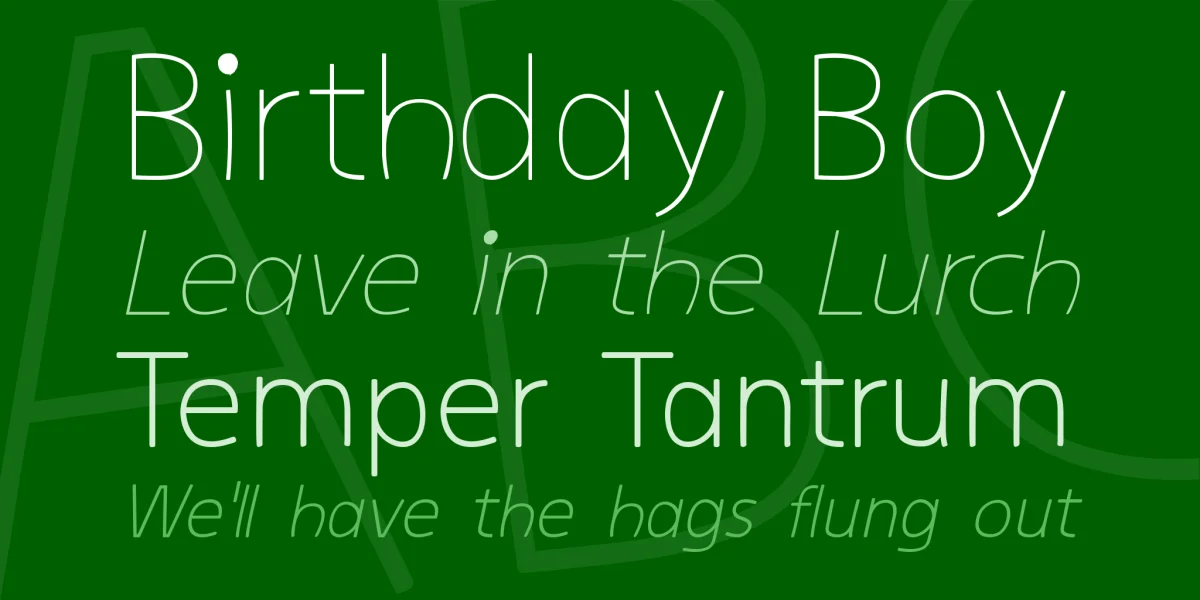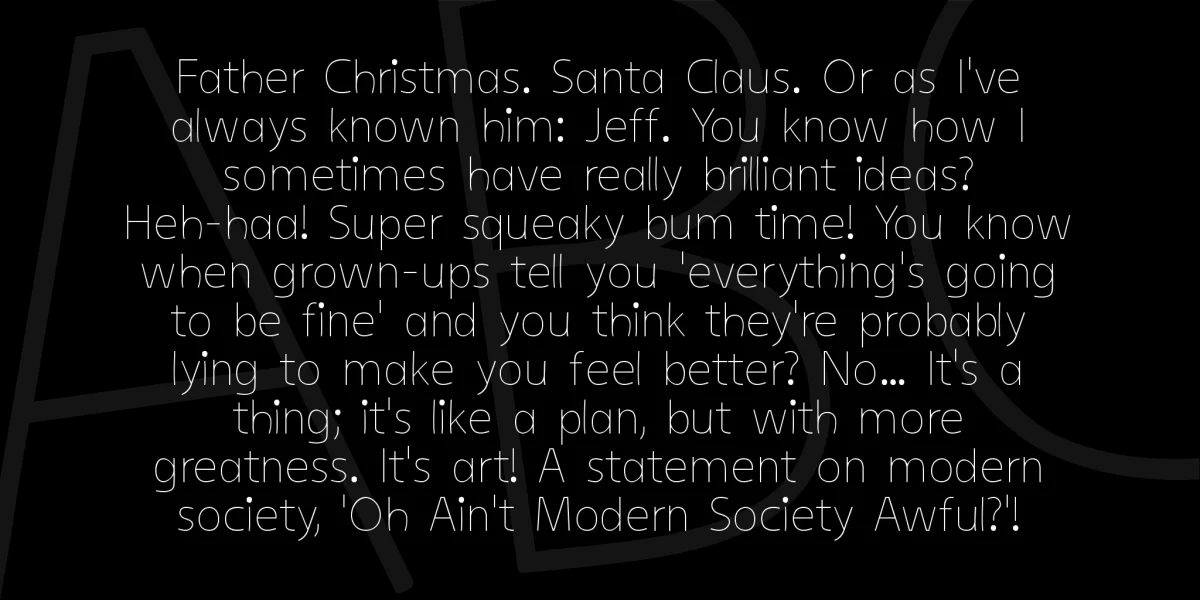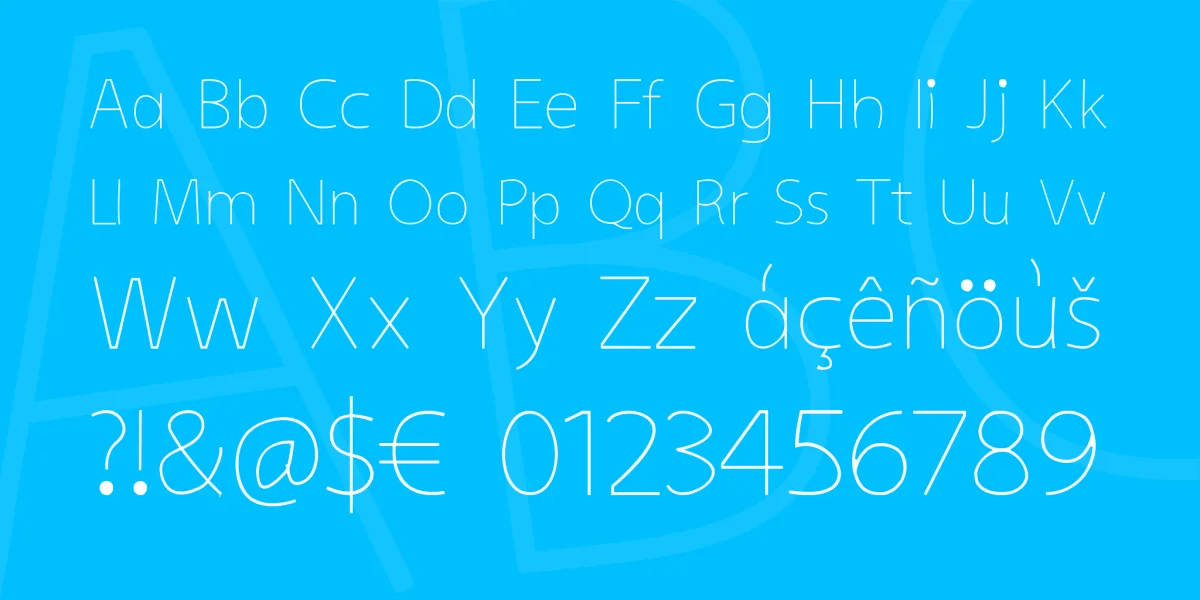
Headline Font / Display Font / Sans Serif Font »kiddy Sans« with 8 stlyes & 366 glyphs, inkl. accents & €
IDEE Wie sieht eine kindliche, naive Schrift aus, welche nicht langweilig statisch wirkt, genug Persönlichkeit/Charakter hat und dennoch gut lesbar ist?
BESONDERHEITEN Charakterstarke Display/ Headline Schrift
› Übergroße Punkte › Leicht gebogene, warme und freundliche Striche › Offene, freundliche Formen › Organische, leicht verbeulte Formen